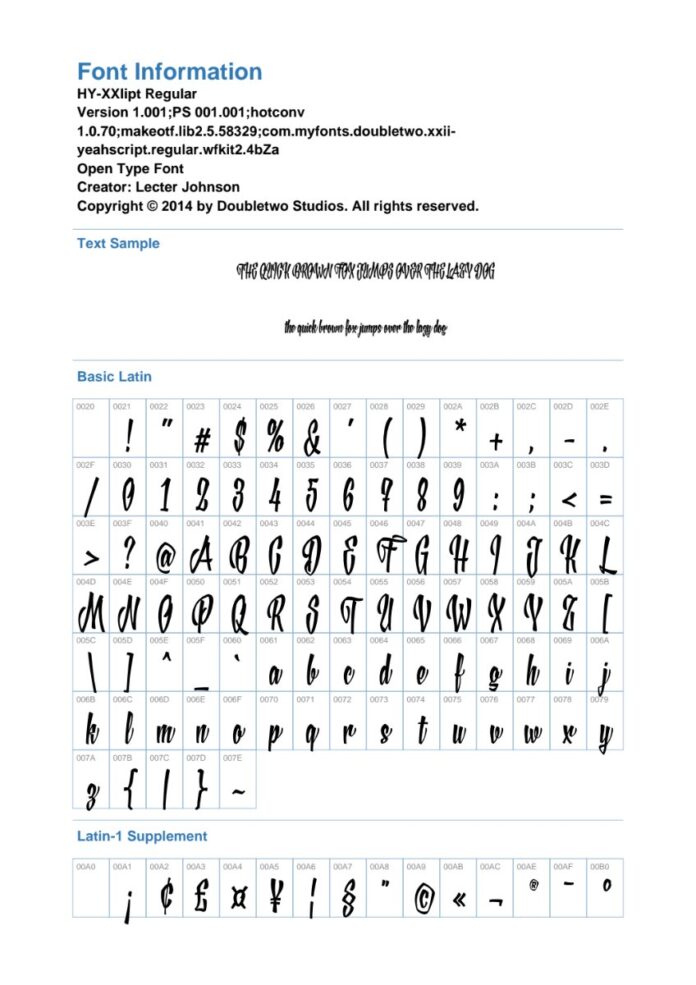
Font Chữ HY-XXIipt Đẹp
Font Chữ HY-XXIipt Đẹp. Khám phá font chữ HY-XXIipt Regular, một lựa chọn tuyệt vời cho các thiết kế sáng tạo. Font chữ này mang đến vẻ đẹp mềm mại, uyển chuyển, phù hợp cho nhiều dự án từ thiệp mời đến logo.
Trong thế giới thiết kế đồ họa, việc lựa chọn font chữ phù hợp có thể tạo nên sự khác biệt lớn cho một dự án. Font chữ không chỉ truyền tải thông điệp mà còn thể hiện phong cách và cá tính của thương hiệu hoặc sản phẩm. Hôm nay, chúng ta sẽ cùng tìm hiểu về một font chữ đặc biệt: HY-XXIipt Regular – một tài nguyên quý giá mà bạn có thể tìm thấy tại Poster.vn.
Giới thiệu về Font HY-XXIipt Regular
HY-XXIipt Regular là một font chữ OpenType được tạo bởi Lester Johnson của Doubletwo Studios. Với thiết kế độc đáo và sự tinh tế trong từng nét chữ, font này nhanh chóng trở thành lựa chọn yêu thích của nhiều nhà thiết kế. Phiên bản 1.001 của HY-XXIipt Regular mang đến sự ổn định và khả năng tương thích cao trên nhiều nền tảng.
Font HY-XXIipt Regular nổi bật với các ký tự viết tay mềm mại, uyển chuyển, tạo cảm giác gần gũi và cá nhân hóa. Các nét chữ được thiết kế tỉ mỉ, mang đến sự thanh lịch và hiện đại, phù hợp với nhiều phong cách thiết kế khác nhau. Từ các dự án mang tính nghệ thuật đến các ấn phẩm thương mại, HY-XXIipt Regular đều có thể phát huy tối đa vẻ đẹp của mình.
Đặc điểm nổi bật của HY-XXIipt Regular
• Phong cách viết tay: Font chữ mô phỏng nét viết tay tự nhiên, mang lại cảm giác ấm áp và thân thiện.
• Tính linh hoạt: Phù hợp cho nhiều mục đích sử dụng như thiệp mời, logo, tiêu đề, bao bì sản phẩm, và các ấn phẩm truyền thông.
• Độ rõ nét cao: Dù là kích thước lớn hay nhỏ, các ký tự vẫn giữ được độ rõ nét, dễ đọc.
• Hỗ trợ đa ngôn ngữ: Ngoài bảng chữ cái Latin cơ bản, font còn hỗ trợ các ký tự Latin-1 Supplement, mở rộng khả năng sử dụng.
Ứng dụng của Font HY-XXIipt trong thiết kế
Với vẻ đẹp độc đáo, HY-XXIipt Regular có thể được ứng dụng trong rất nhiều lĩnh vực thiết kế. Dưới đây là một số gợi ý:
Thiết kế thương hiệu và logo
Nếu bạn đang tìm kiếm một font chữ để tạo ra một logo mang tính cá nhân hóa và độc đáo, HY-XXIipt Regular là một lựa chọn tuyệt vời. Các nét chữ mềm mại có thể giúp thương hiệu của bạn trở nên gần gũi và dễ nhớ hơn. Đặc biệt, font này rất phù hợp cho các thương hiệu liên quan đến thời trang, làm đẹp, ẩm thực, hoặc các dịch vụ thủ công.
Thiệp mời và ấn phẩm cá nhân
Với phong cách viết tay, HY-XXIipt Regular là lựa chọn lý tưởng cho thiệp cưới, thiệp sinh nhật, thiệp chúc mừng hoặc các ấn phẩm cá nhân khác. Font chữ này sẽ giúp truyền tải thông điệp một cách chân thành và tinh tế, tạo ấn tượng mạnh mẽ cho người nhận.
Thiết kế bao bì sản phẩm
Để sản phẩm của bạn nổi bật trên kệ hàng, bao bì đóng vai trò rất quan trọng. Sử dụng HY-XXIipt Regular trên bao bì có thể tạo ra một vẻ ngoài cao cấp, thủ công và độc đáo, thu hút sự chú ý của khách hàng. Font chữ này đặc biệt phù hợp cho các sản phẩm thủ công, thực phẩm hữu cơ, hoặc các mặt hàng có giá trị nghệ thuật.
Thiết kế website và blog
Trong thiết kế web, việc sử dụng font chữ phù hợp có thể cải thiện trải nghiệm người dùng. HY-XXIipt Regular có thể được sử dụng cho các tiêu đề hoặc các đoạn văn bản ngắn để tạo điểm nhấn, mang lại cảm giác thân thiện và dễ chịu cho người đọc.
Cách sử dụng Font HY-XXIipt hiệu quả
Để tận dụng tối đa vẻ đẹp của HY-XXIipt Regular, bạn cần lưu ý một số điểm sau:
• Kết hợp với font chữ khác: HY-XXIipt Regular thường đẹp nhất khi được kết hợp với một font chữ sans-serif hoặc serif đơn giản để tạo sự cân bằng và dễ đọc.
• Kích thước phù hợp: Do có nhiều chi tiết, font này thường phù hợp với các kích thước lớn hơn cho tiêu đề hoặc logo. Khi sử dụng cho đoạn văn bản dài, hãy đảm bảo kích thước đủ lớn để dễ đọc.
• Màu sắc: Lựa chọn màu sắc phù hợp sẽ làm nổi bật vẻ đẹp của font. Các tông màu pastel, màu đất hoặc màu sắc tương phản nhẹ nhàng thường rất phù hợp.
Font HY-XXIipt phù hợp với loại thiết kế nào?
Font này rất phù hợp cho thiết kế logo, thiệp mời, bao bì sản phẩm, tiêu đề website, và các ấn phẩm cá nhân cần sự tinh tế và độc đáo.